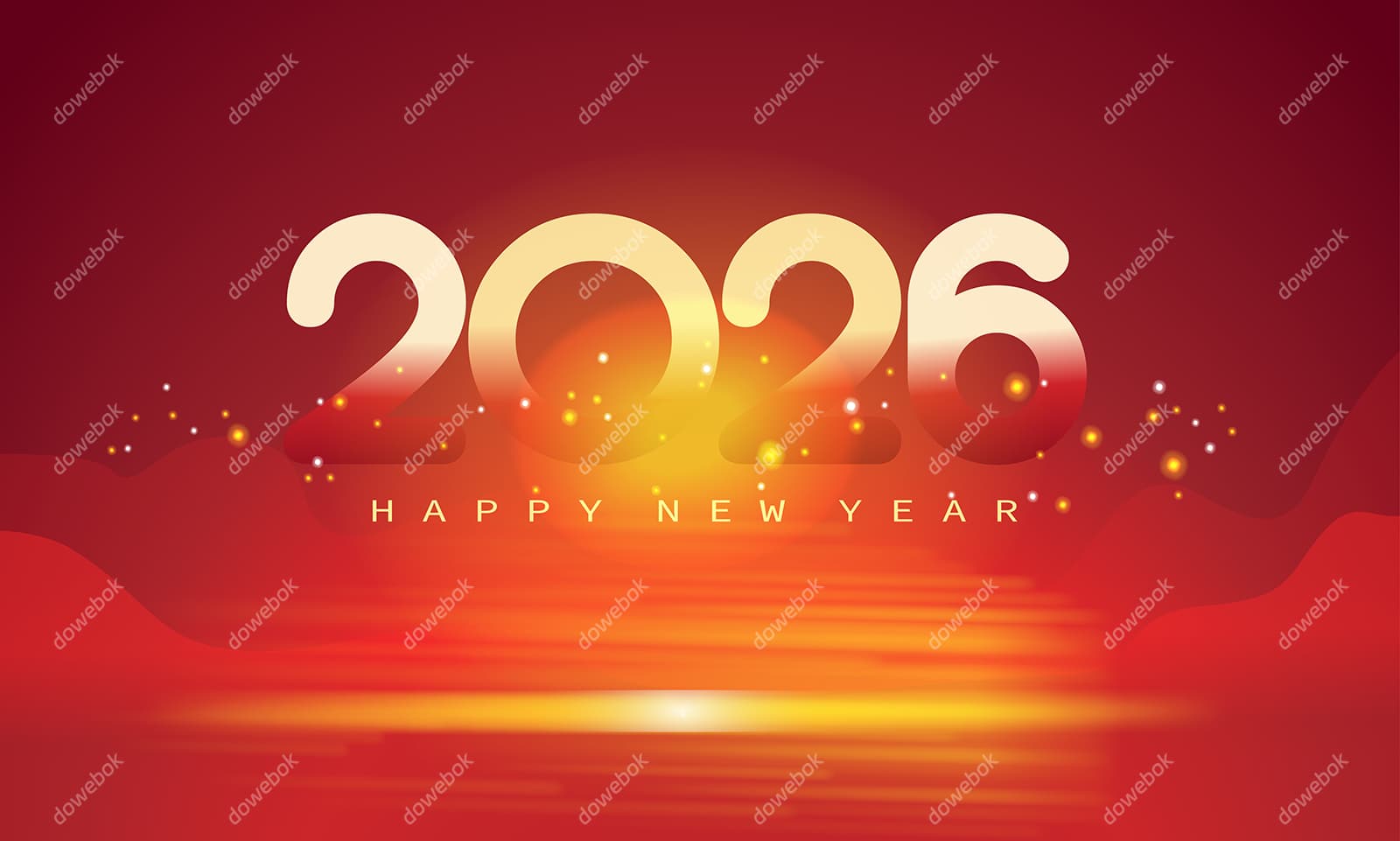
这是一款暖红渐变背景和星光设计 2026 新年快乐矢量素材,暖红渐变背景晕染出热烈氛围,底部光影似鎏金波纹,添了灵动质感。“2026” 以白金渐变呈现,边缘裹着星点光斑,醒目亮眼。下方衬着简约的 “Happy New Year”,整体以暖色调 + 闪耀细节,既显跨年的盛大喜庆,又用柔美的光影层次透出雅致的节日质感,热烈且精致。